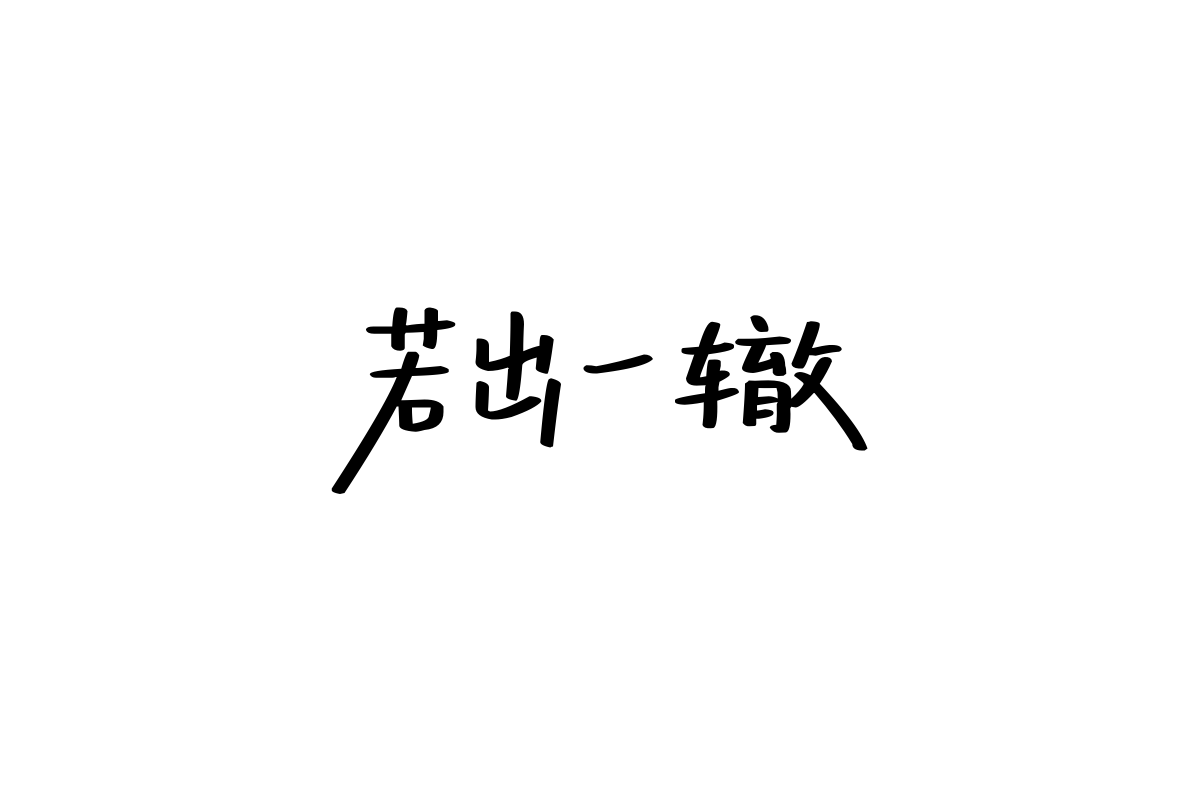
造字工房书言体,是一款由中国设计师李斌创作的书法字体。这款字体以其独特的艺术风格和优美的线条而受到广泛欢迎。
造字工房书言体的笔画流畅自然,字形结构严谨,既有传统的韵味,又不失现代感。它的每个字符都经过精心设计和雕琢,形成了一种独特的视觉美感。无论是用于印刷、广告还是设计作品,都能展现出其独特的魅力。
这款字体适用于各种场景,包括网站、海报、名片、包装等。它不仅能够提升设计的品味,还能够增加作品的吸引力。无论是个人还是企业,都可以使用造字工房书言体来展现自己的独特风格。